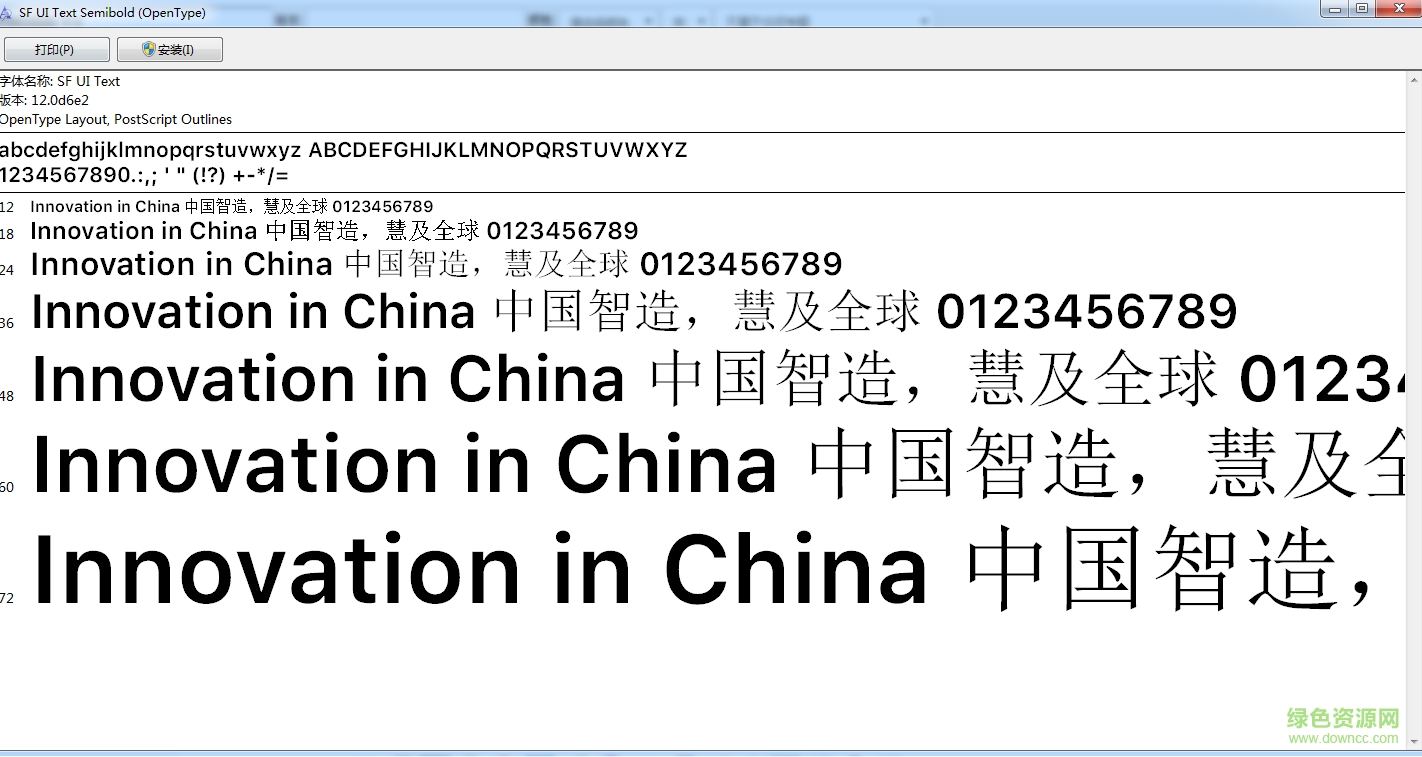
sfuitext semibold字體是一款設(shè)計(jì)精致的ios系統(tǒng)字體,該字體字形秀美,結(jié)構(gòu)均勻,排版效果出色,十分符合字體構(gòu)形規(guī)律,可用作廣告字體或海報(bào)字體,歡迎大家在綠色資源網(wǎng)下載!
在iPhone,iPad,iWatch 中設(shè)置的Body字體不應(yīng)該小于11pt,這樣才能被正常閱讀。我們推薦的Body文本大小應(yīng)該在15-18pt。
當(dāng)我們設(shè)置更大的字體來獲得更好的易讀性的同時(shí),我們也應(yīng)相應(yīng)地減小字體的字重(粗細(xì)),考慮Light,Thin或者Ultra Thin。過重的字體會(huì)太過醒目,從而影響其他內(nèi)容的顯示效果。